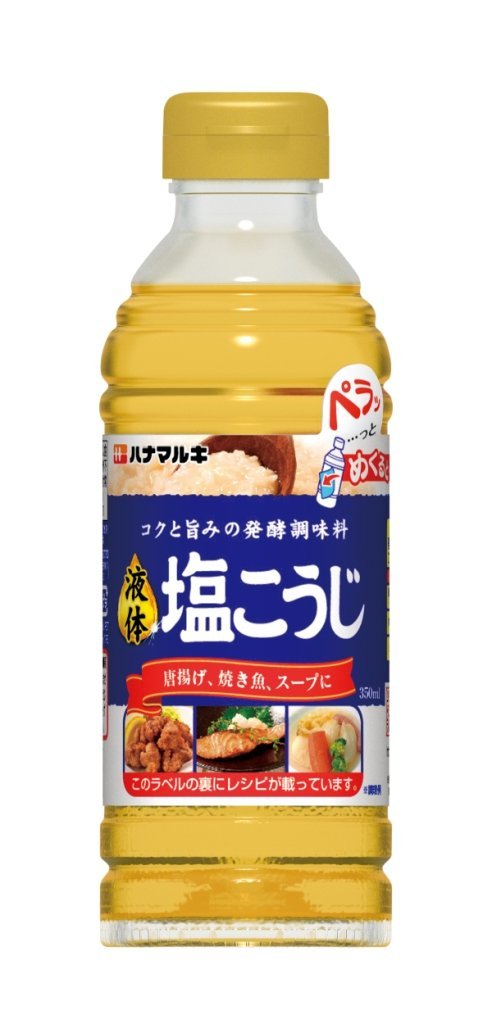
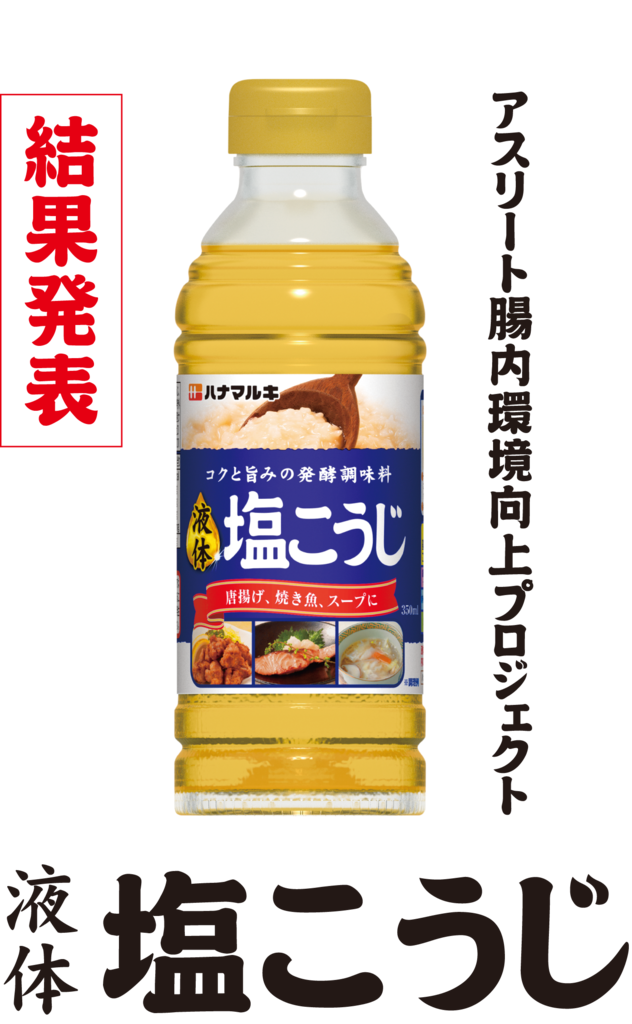
▼AuB株式会社
今回のプロジェクトを通じて、液体塩こうじの摂取によって免疫力に関する菌が有意に向上したことが確認されました。アスリートは強度の高いトレーニングにより免疫力が下がりやすく、風邪などを引きやすい傾向にありますので、有益な結果が得られたと言えます。
また、今回増加が見られた短鎖脂肪酸を産生する菌については、ラットの実験で運動によって増加することを示した既報の論文もあり、弊社ではヒトでも同様の傾向があることを確認して学会で発表した実績があります。
今回の結果は、アスリートにとって非常に有効なデータを取得できたと考えております。またこれから冬本番、インフルエンザなどの流行も危惧される中、液体塩こうじを使用したバリエーション豊かな食生活をおくることで腸から健康になって、皆様に元気に過ごしていただきたいです。
液体塩こうじならハナマルキ
「液体塩こうじ」は粒状の塩こうじをハナマルキ独自の製法(特許取得)で液体にした塩こうじ。こうじに含まれる酵素の働きによる「素材のうま味を引き出す」特徴があり、
液体化することによって、肉・魚の下味から、煮物・炒め物などの味付けまで、調味料として幅広く使用できる。
液体塩こうじは、ハナマルキの独自技術を使い、製造過程で加熱をしない製法で製造しているため、こうじの酵素が活発に働き、素材のうま味を引き出し、柔らかさを増している、まさに「液体塩こうじならハナマルキ」なのだ。
ハナマルキの「塩こうじ」製品のタイトルの文字は「ダイナフォント円楷書」が採用
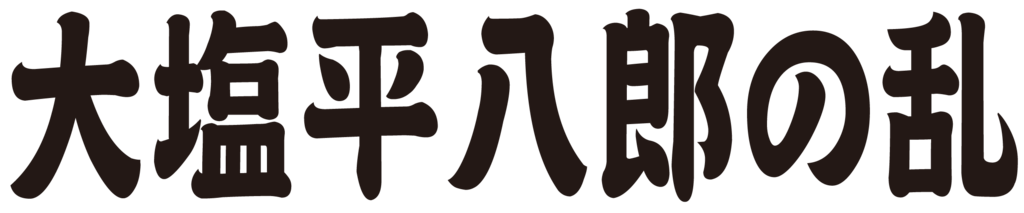
「ハナマルキ 液体塩こうじ」などハナマルキの「塩こうじ」製品のパッケージタイトルの文字にダイナフォントの円楷書が長体をかけて採用されている。
円楷書
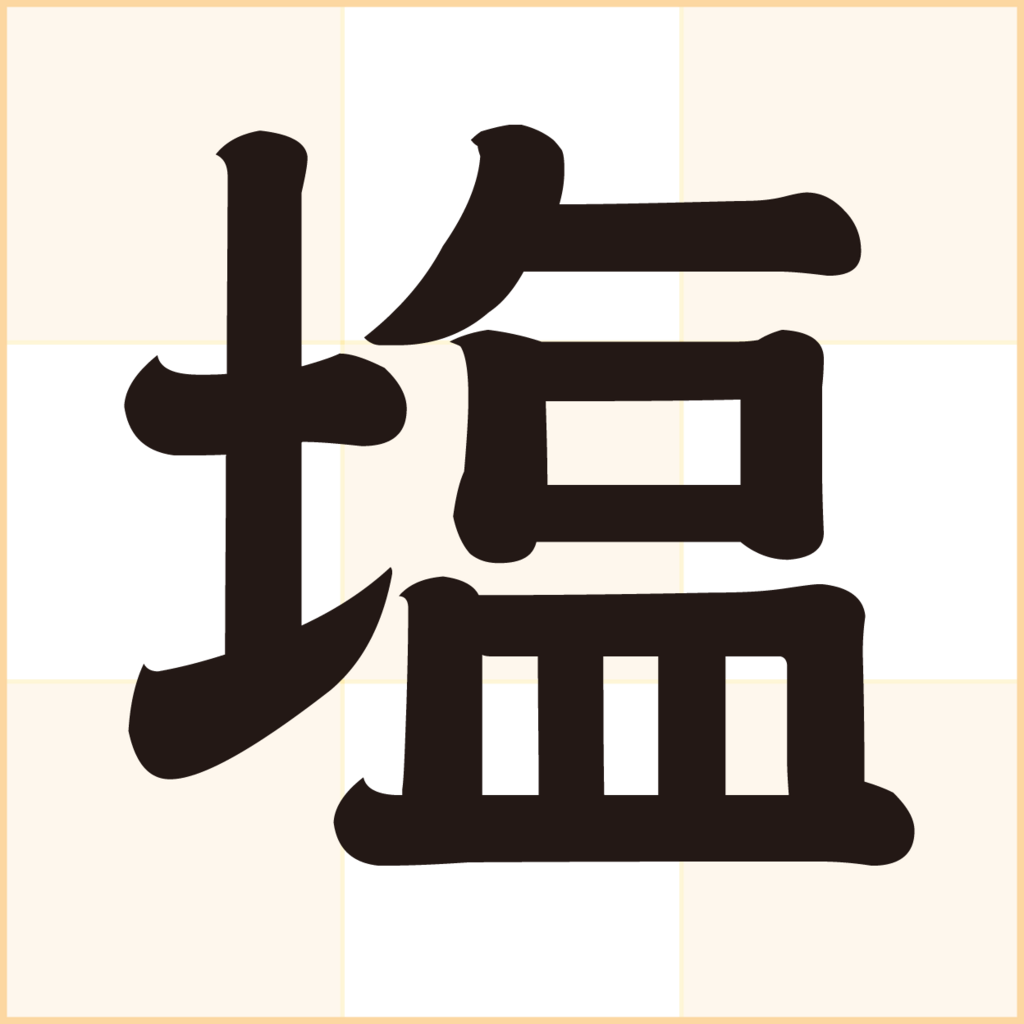
太く丸みのある筆勢により穏やかな一面と力強さを兼ね備えた楷書体。
円楷書はダイナコムウェアが開発・販売するダイナフォント(DynaFont)シリーズのフォント(書体)であり、有料フォントとなっている。